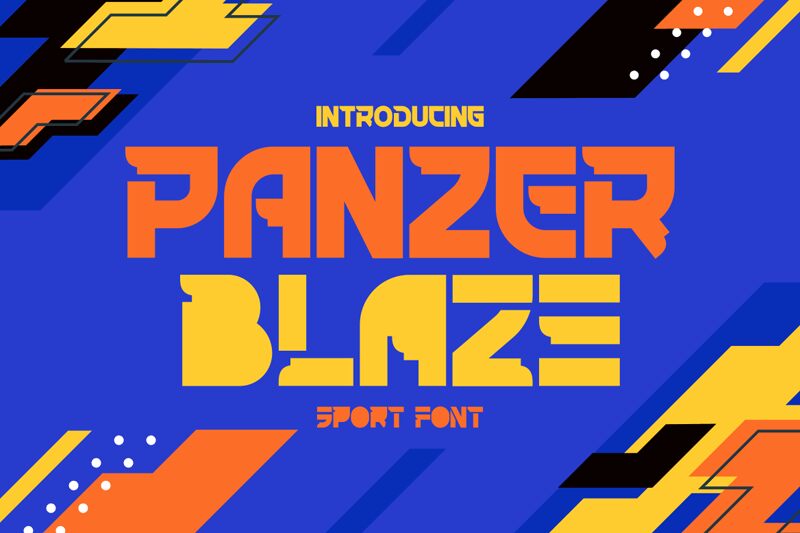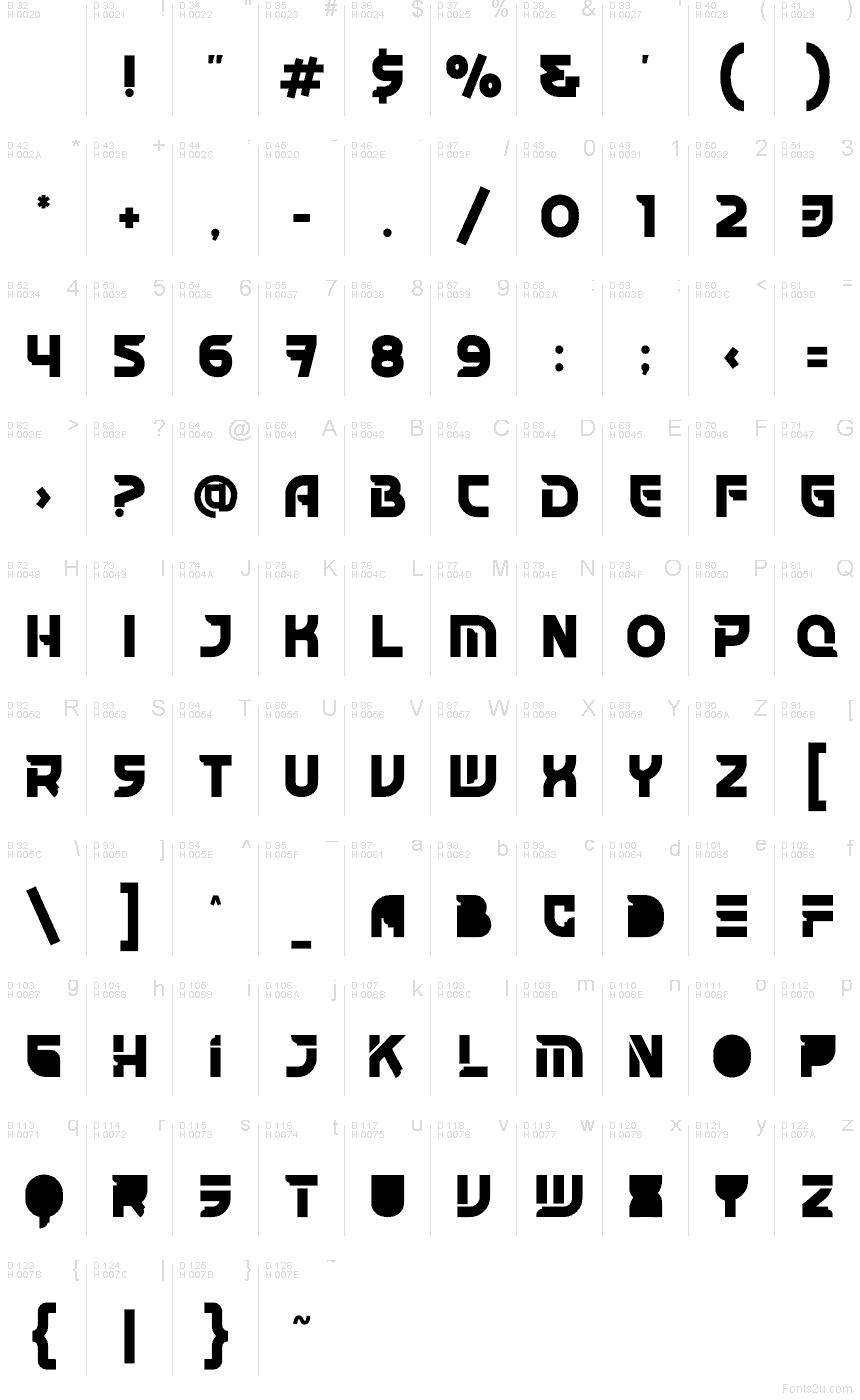
Panzer Blaze od Shanaf Studio je bezplatné techno titulkové písmo s ostrými hranami a futuristickým charakterom. Veľké písmená pôsobia ako postavené z ťažkých geometrických blokov, rezaných ostrými diagonálnymi zárezmi a horizontálnymi medzerami, ktoré dodávajú znakom rýchly, strojový rytmus.
Hodí sa na plagátové nadpisy, herný branding, hudobné obaly, sci-fi titulky a e-športovú grafiku, kde krátke slová potrebujú ten obrnený, technický vzhľad. Keďže je to bezplatné písmo, skvele funguje aj v logách a monogramoch, pretože písmená do seba zapadajú s kompaktným a výrazným vzhľadom a opakujúce sa rezy dodávajú tvarom dynamiku.
Prezentácia a vizuálna ukážka písma Panzer Blaze
Mapa znakov písma Panzer Blaze
Mapa znakov písma Panzer Blaze: Základná latinka, strana 1
Glyfy písma Panzer Blaze — Základná latinka, strana 1